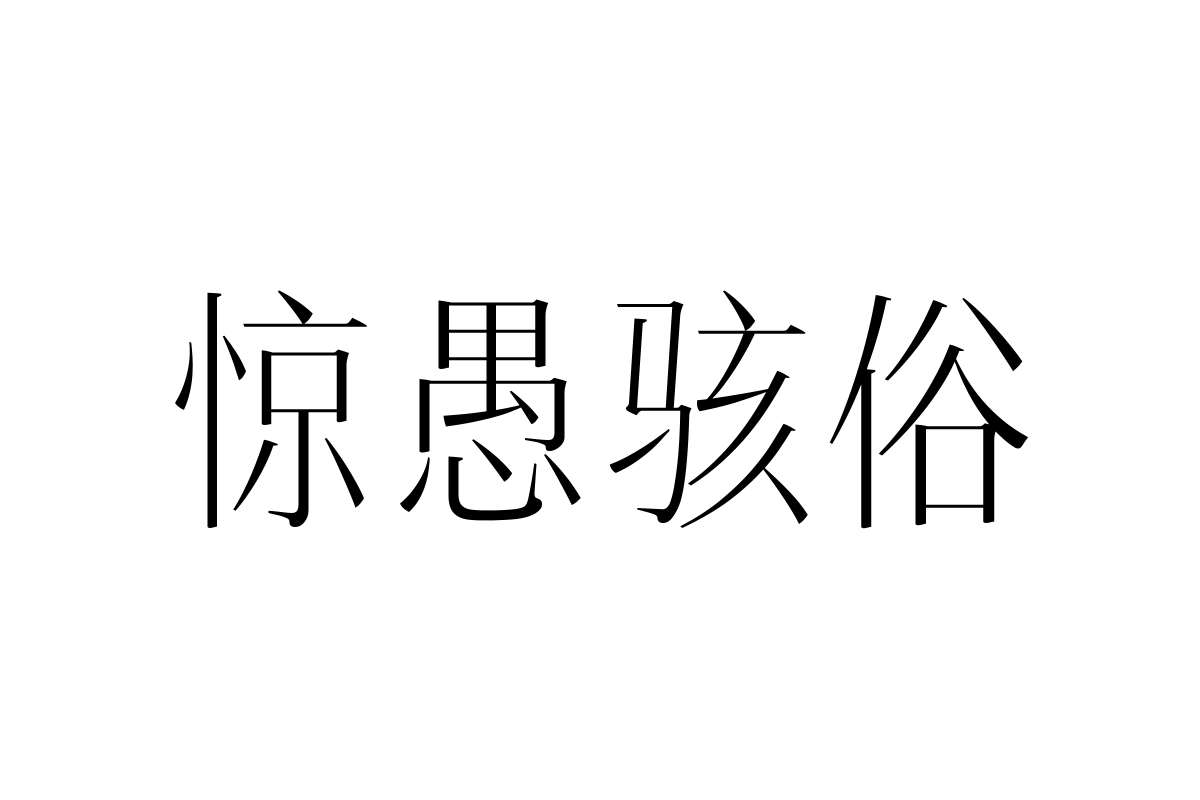
汉仪瑞意宋X 35W是一款专为中文排版设计的字体,具有现代感和艺术气息。它的特点是字形简洁、线条流畅,适合用于广告、杂志、书籍等各类出版物的标题、正文和装饰性文字。这款字体的设计灵感来源于中国传统文化元素,如汉字、书法、绘画等,因此具有很强的文化内涵和艺术价值。同时,汉仪瑞意宋X 35W的可读性和美观性都非常出色,是设计师们常用的字体之一。